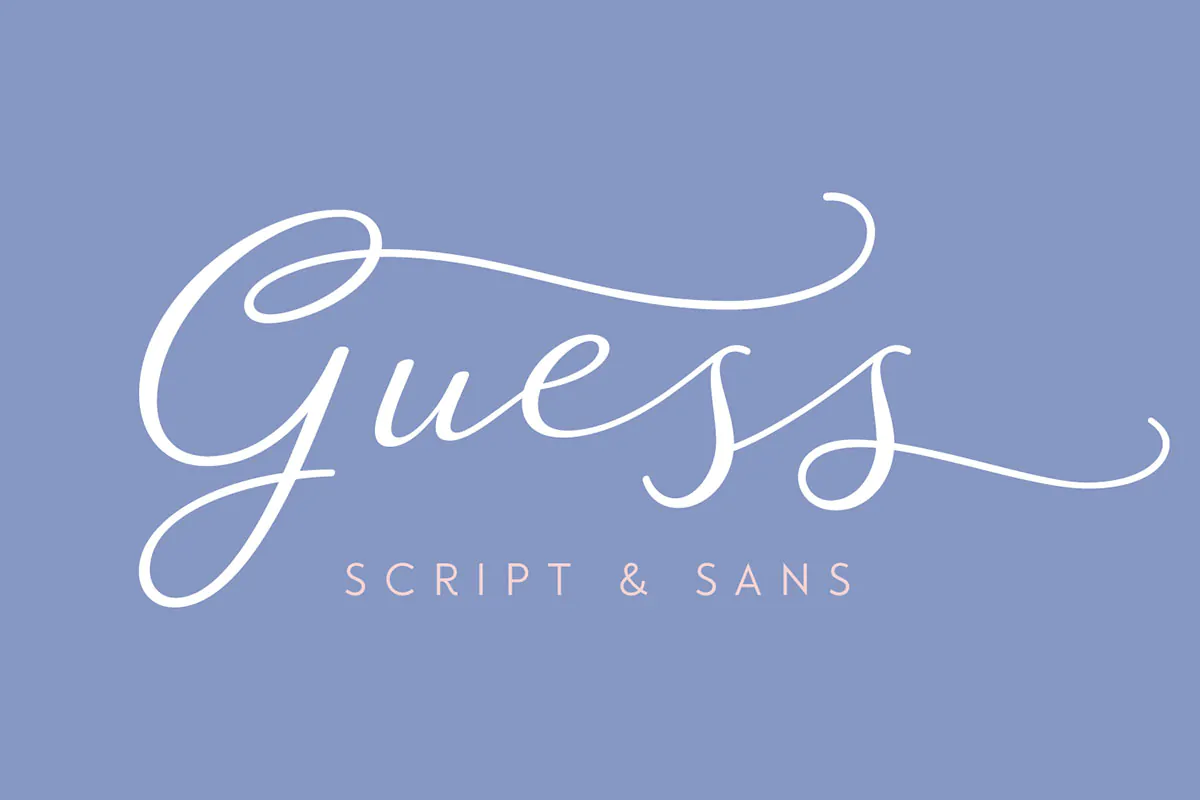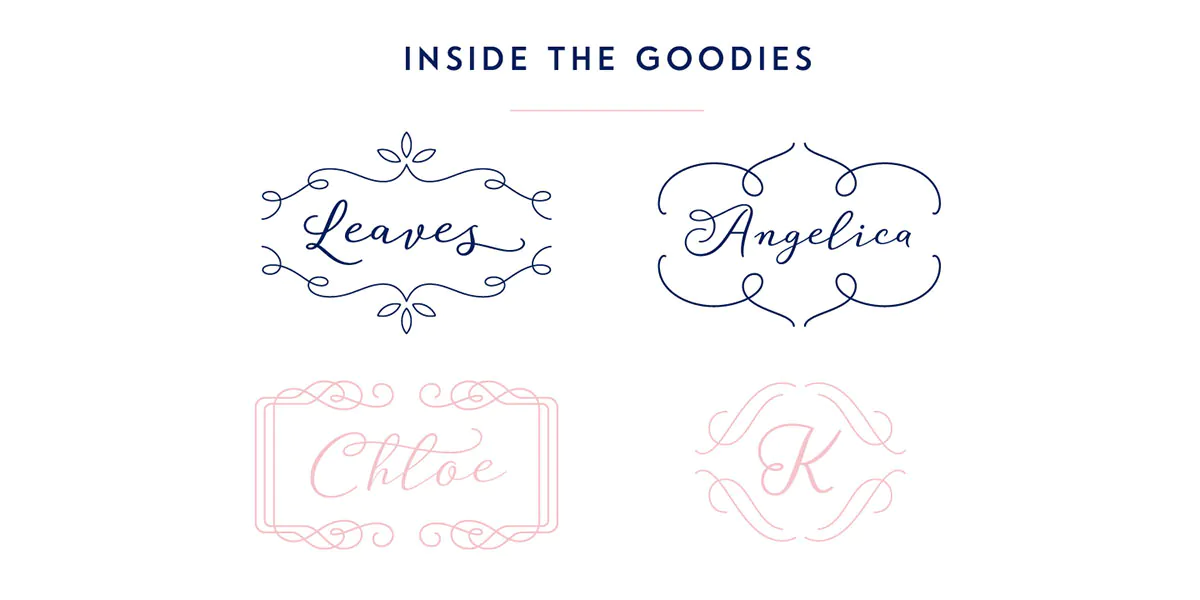
فونت خوشنویسی و پیوسته نویسی
فونت خوشنویسی و پیوسته نویسی Guess یک قلم دوتایی و دستنویس خانواده دار فوق العاده زیبا است که مناسب برای استفاده در طرح و پروژههای مختلف همچون طراحی پوستر، بنر، بسته بندی محصولات، آرایشی و بهداشتی و … میباشد.